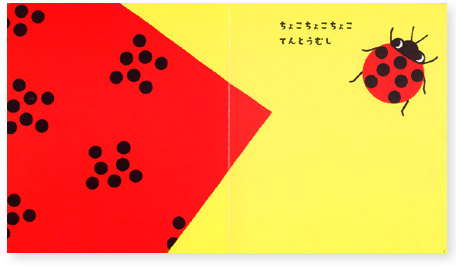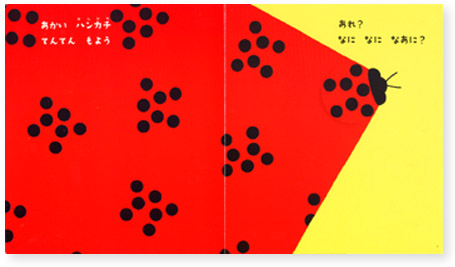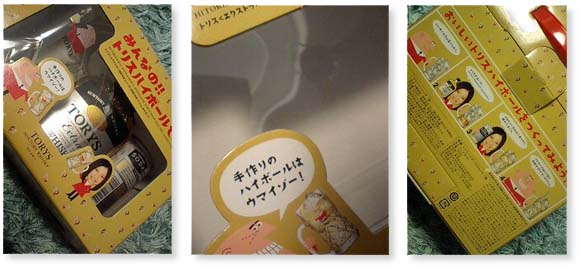
夏休みワークショップのDM
先日届いた、味岡伸太郎氏からの
ワークショップのDM。 自分の書体で、すべてを創る味岡氏が 珍しく、私の書体、笑点角を使ってもらってました。 間を生かした文字の配置、さすがです。 宛名面も横一列に組まれた素材の冒険の 「の」の字を上に揃えて下にルビ、にくいね。 |
書体:笑点角
トリスハイボールパッケージ
キリギリス書体が使われていると
書体:キリギリス
なになになあに?
作:木坂涼 絵:田代卓 発行所:フレーベル館 |
子どものことばを引きだし、
書体:キリギリス
月刊誌choice
書体:フラミング
やせる!冷えとり習慣
書体:キリギリス
書体:フラミング
他にもこんな本にも使われているようです。
書体:マユミンウォーク
通園通学の手づくりレシピ
こころNo.1とマユミンウォーク 使っていただきました。感謝。 |
和のスイーツ
書体:こころNo.1
セキユリティいろはかるた
デザイン:ヨーヨーラランデーズ/川井ララ セキュリティのイロハを「い」「ろ」「は」で始まる48の句で まとめているカルタです。 パソコンユーザーが知っておくと便利なケーススタディを、 かるたにまとめたものです。 川井ララさんからこころ書体を使用しいたのでということで 販売もされているようです。 |
Yuzukoのぷくぷくマスコット